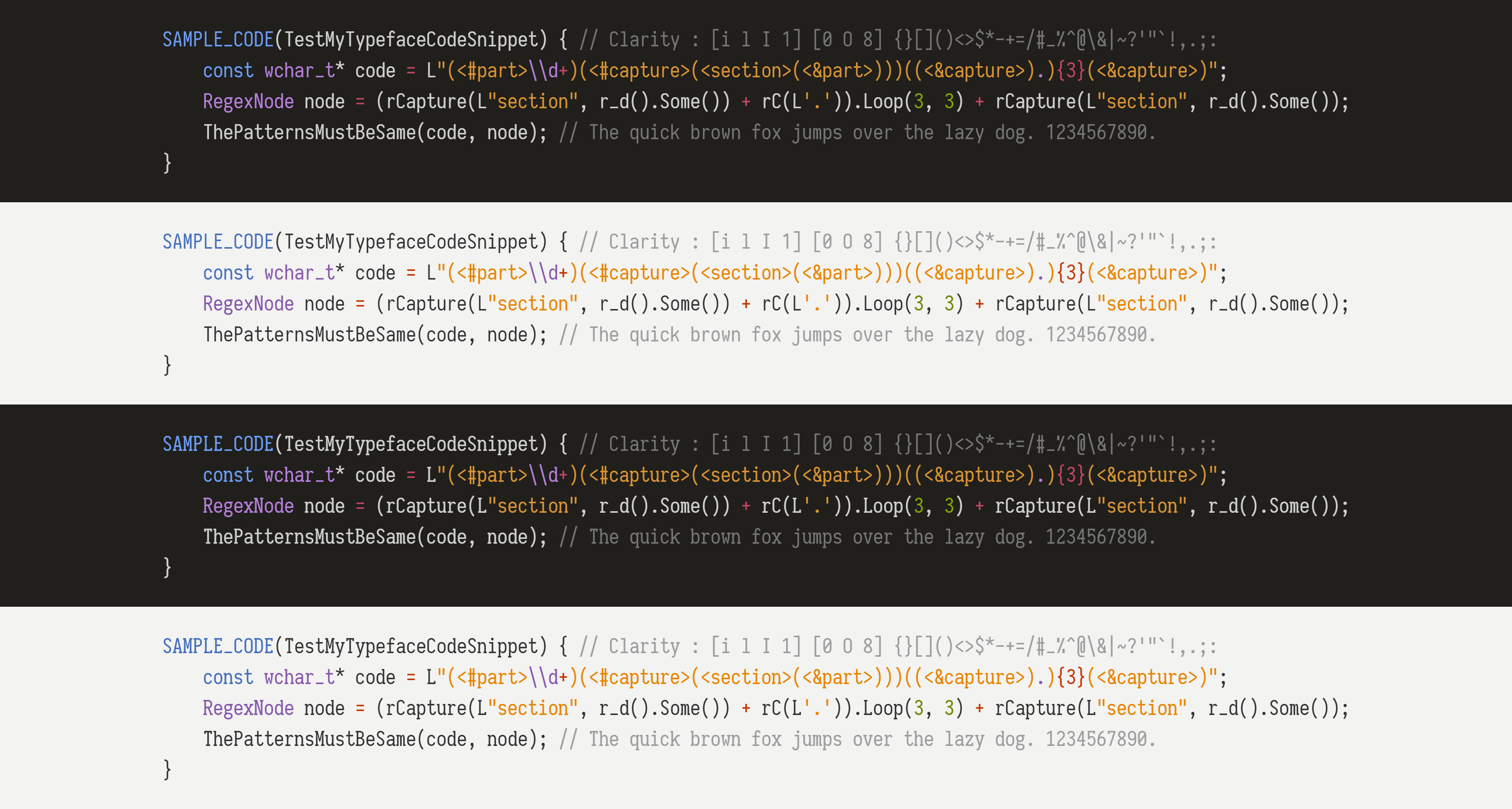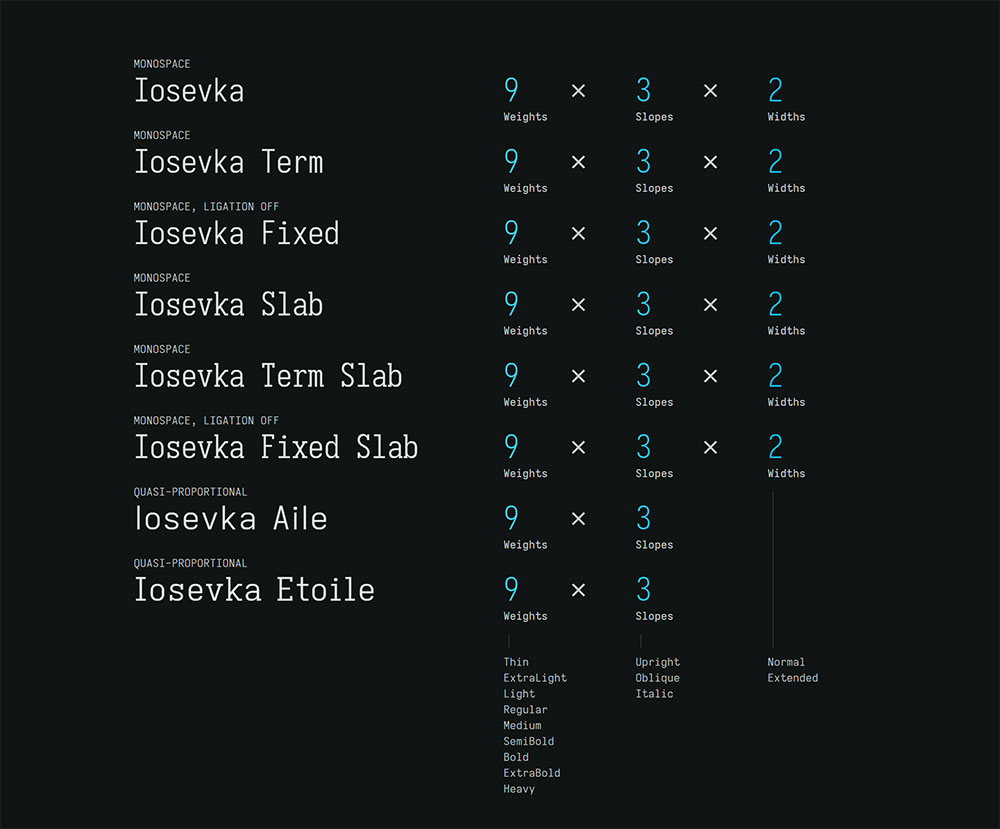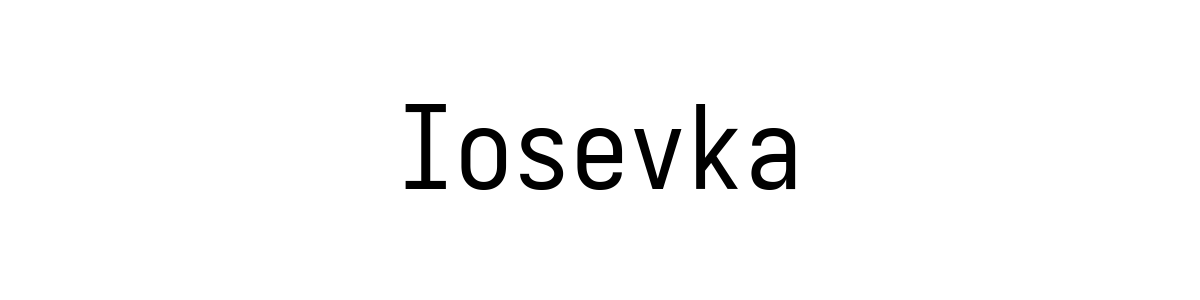
Iosevka
Iosevka 是一款为现代编程环境打造的高度可定制等宽字体,该字体专为代码编辑而生,核心设计目标是在有限的水平空间内显示更多字符,同时确保易读性。字形采用窄高比例,在同等字号下能比常规等宽字体容纳更多列代码。
对易混淆字符(如 oO0iIl1)进行了显式区分,Iosevka 有非常多的字形可供选择,衬线/非衬线,多级字重,不同风格的斜体,甚至还有融合了其他常用编程字体设计风格的风味版本。
字体风格
Iosevka 的风格特征是紧凑与高效,窄高的字形结构是其最鲜明的视觉标识,直接服务于提升代码编辑器的信息密度。在字形设计上,它追求一种冷静、中性的技术美感,笔画处理干净利落,既有无衬线体的直接明了,也提供衬线体的细微引导。